在古时牌匾指示、文化的标志。某种意义上象征着权利、地位。在宫殿、牌坊、寺庙、中国的一些古建筑、中式风格的装修,牌匾都高高地悬挂在显眼的位置。
现在牌匾主要用于商业领域,变成传播商业信息的一种广告形式。由于牌匾是长期使用的,细节必定要做的精致无缺的,牌匾的字体设计更是更是重中之重,在通过软件设计成 图片字体 的样式必须是按照要求能开展手工雕刻的。
那么问题来了,适合商业牌匾设计的字体到底有哪些呢?不如小编来给大家推荐两款适用字体吧!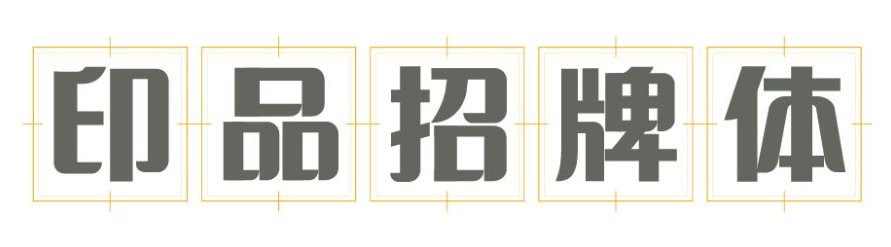
印品招牌体 :这款字体,笔画粗壮,略带有纤细笔触,字型紧聚但不失美感。在弯钩处都做了线条处理,看起来不会死板。长时间观看也不会产生视觉突兀,给人一种浑厚有力的感觉。作为招牌字会有一种踏实感。
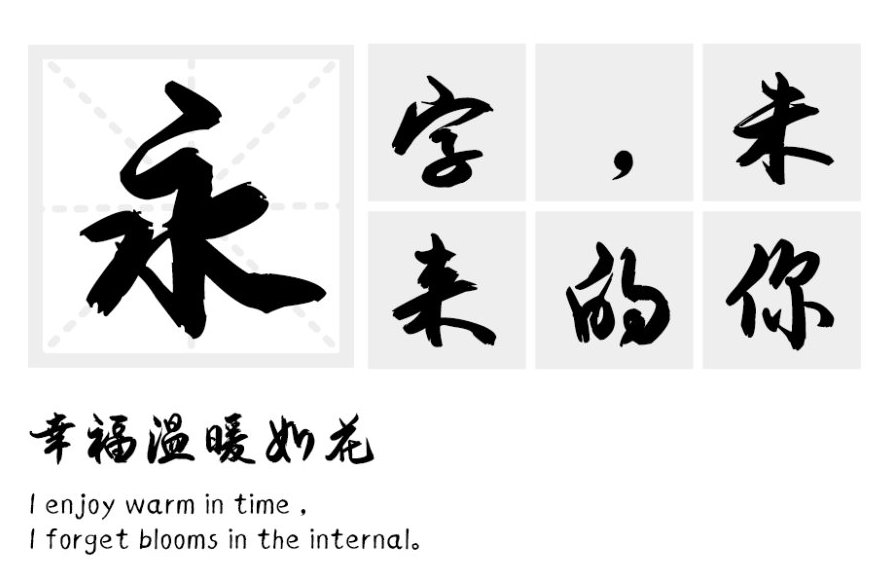
安景臣毛笔行书:这是一款毛笔行书,笔风处处透露着深厚的传统功力,在这传统的基础上又融入了现代的审美气息。比起传统的行书,规范工整了许多,规范也不失行书特色。字型作为招牌会更易于 识别字体 。